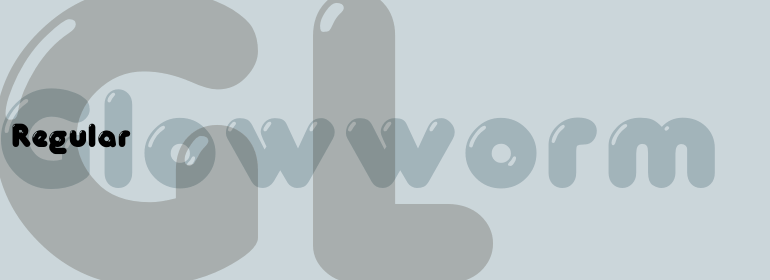
Glowworm
Glowworm,这款字体结构工整、笔画清晰,兼顾美观与易读性,适用于标题、正文、海报、包装、LOGO 等多种场景。字形优雅稳定,风格百搭耐看,适配日常排版与创意设计,让文字呈现更舒适、更具质感。Glowworm一笔一画,皆是细节,以均衡的比例、流畅的线条打造舒适视觉体验,字形端正大气,风格简约现代。无论是商业设计、品牌宣传还是日常排版,都能轻松驾驭,让文字更有格调与力量。Glowworm字体下载。
字体品牌: Monotype 设计师:暂无 字体分类:衬线体 字体属性:外文 字符集:Unicode 发布时间: 2018